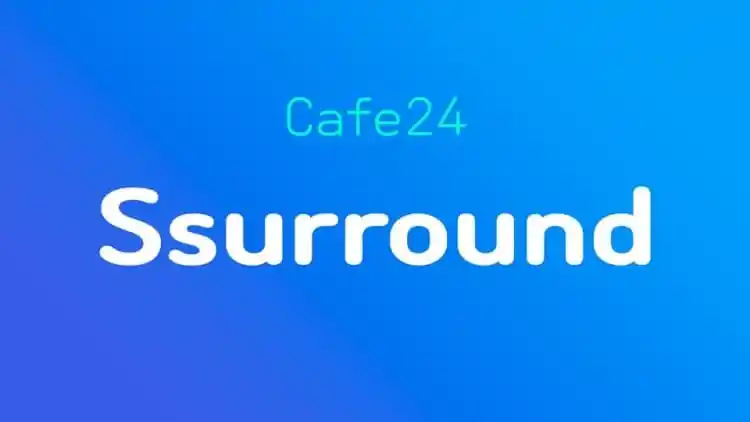
A Ssurround Sans Serif Font é uma elegante tipografia sans serif que traz consigo um toque refinado. Além disso, a fonte transmite uma sensação de conforto e familiaridade que remete ao lar. É produzida pela Cafe24, uma das maiores plataformas de negócios online no mundo. Sua família está composta por um conjunto de letras com estrutura geométrica simples e formas arredondadas. Essa tipografia é perfeita para construir marcas, pois tem um estilo limpo e amigável que permite a criação de uma identidade visual forte e imediata. O resultado final resultará em uma aparência moderna, sofisticada e acolhedora. Ideal tanto para websites quanto para logotipos e materiais gráficos, esta fonte é perfeita para quem procura algo que combine elegância com simplicidade geométrica. A Ssurround Sans Serif Font da 99designs é uma opção de alta qualidade para designers profissionais e amadores buscando um equilíbrio entre modernidade e conforto.